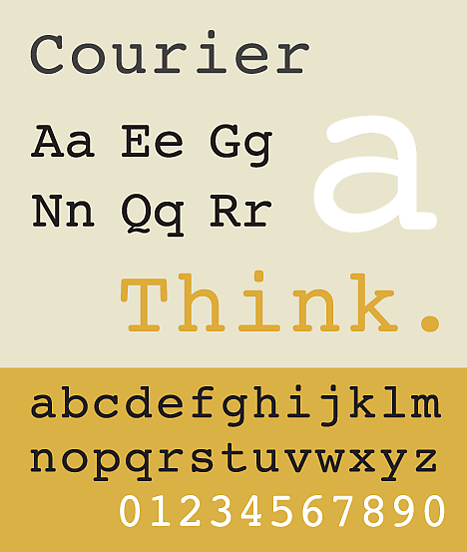
Брусковый шрифт
История
«Первые брусковые шрифты появились в Англии в начале XIX века. В соответствии с формой овалов и засечек, наличием или отсутствием контраста и степенью разноширинности брусковые шрифты делятся на подгруппы „Египетских“, „Геометрических“, „Гуманистических“ брусковых шрифтов и брусковых шрифтов типа „Кларендон“. Кроме того, в эту группу также иногда относят брусковые шрифты с обратным контрастом („Итальянские“)»[3].
Шрифты этого типа занимают ведущее место по шкале читабельности и идеально подходят для набора длинных текстов, так как имеют очень слабый контраст. Однако страница, набранная этим шрифтом, выглядит значительно «темнее» страницы, набранной обычной гарнитурой, поскольку штрихи брускового типа плотнее и более единообразны по толщине. Брусковый шрифт часто используется при наборе детских книг[4].